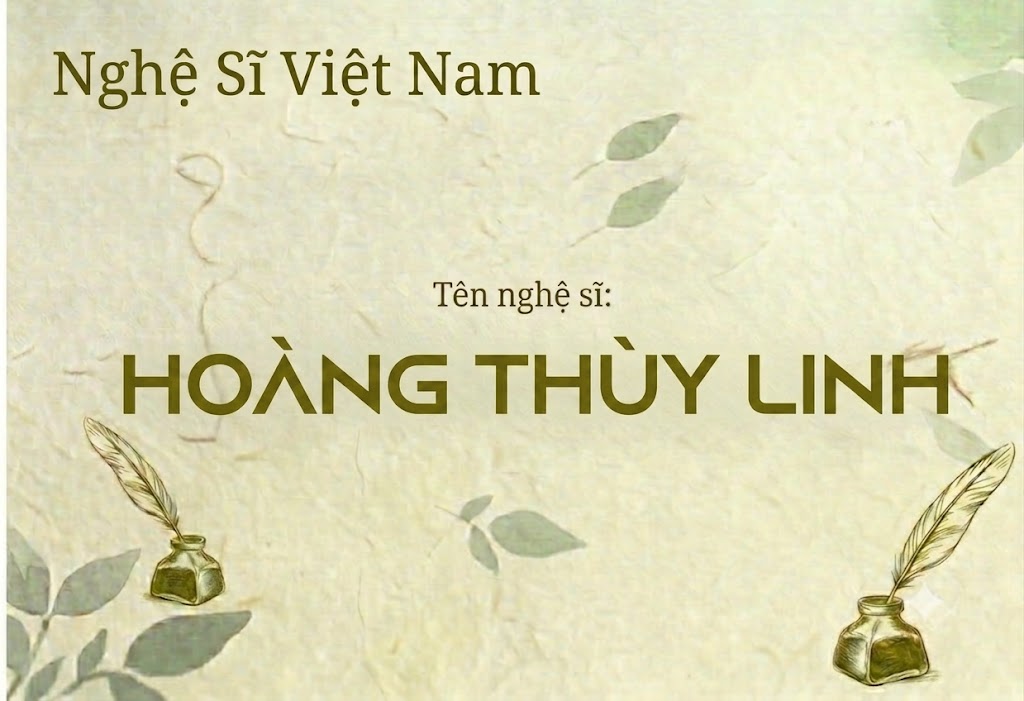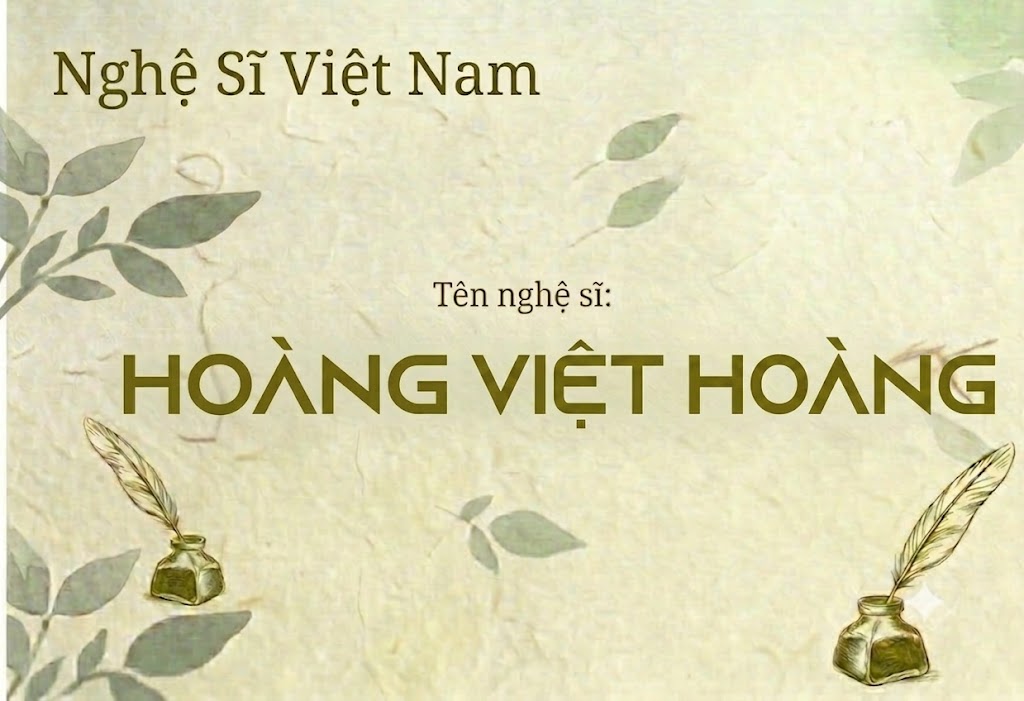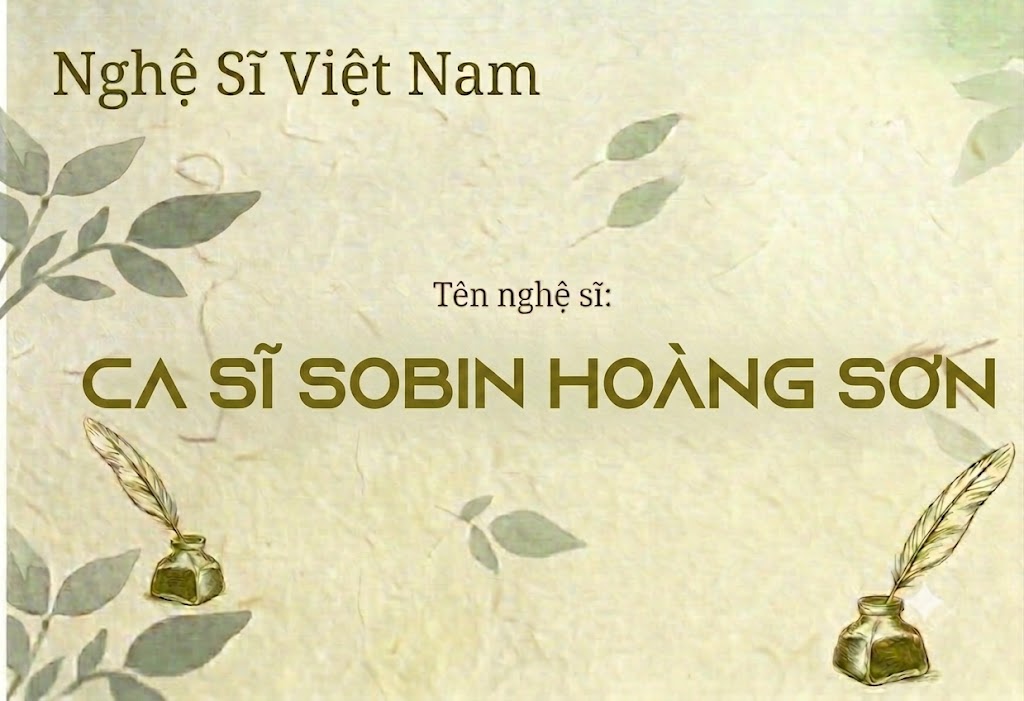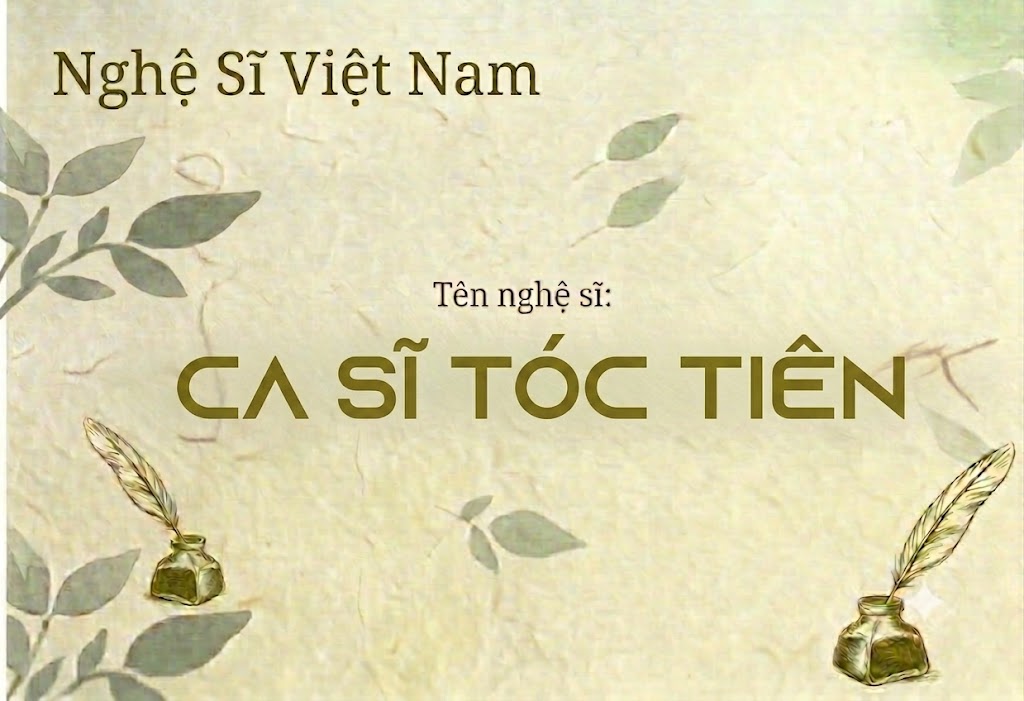
1FTV VIP Azonix
Trong các xu hướng thiết kế đồ họa hiện đại, phong cách tối giản kết hợp với hơi hướng công nghệ tương lai luôn có sức hút mạnh mẽ.
Để tạo nên những ấn phẩm truyền thông độc đáo, việc lựa chọn một phông chữ làm tiêu đề mang tính bứt phá là vô cùng quan trọng.
Nếu bạn đang tìm kiếm một bộ chữ không chân mang phong cách sci-fi đầy hiện đại cho các dự án của mình, thì font 1FTV VIP Azonix chính là sự lựa chọn hoàn hảo.
Giới thiệu về font 1FTV VIP Azonix
Font 1FTV VIP Azonix là một phông chữ display không chân được thiết kế theo xu hướng tối giản và đậm chất công nghệ tương lai.
Đặc điểm nổi bật của phong cách thiết kế Azonix
Sức hút khác biệt của font 1FTV VIP Azonix đến từ cấu trúc hình học vuông vắn kết hợp cùng các đường cắt góc vô cùng táo bạo.
Điểm nhấn độc đáo nhất nằm ở các ký tự như chữ A được cách điệu lược bỏ thanh ngang, tạo nên phom dáng giống như một dấu mũi tên hướng lên đầy cá tính.
Phông chữ được xây dựng theo định dạng all-caps (viết hoa toàn bộ), giúp tạo ra sự đồng đều tuyệt đối về mặt cao độ và bố cục khi sắp xếp dòng tiêu đề.
Nét chữ có độ dày vừa phải, khoảng trống bên trong được tính toán khoa học giúp văn bản luôn giữ được sự thanh thoát, tinh tế và không bị rối mắt.
Để phông chữ vận hành mượt mà trên hệ thống máy tính, phiên bản font 1FTV VIP Azonix đã được xử lý kỹ lưỡng về mặt thông số kĩ thuật.
Hệ thống khoảng cách chữ và độ giãn dòng đã được căn chỉnh chuẩn xác, giúp các từ hiển thị liền mạch và đẹp mắt trên mọi phần mềm biên tập.
Bên cạnh bộ chữ cái viết hoa đồng bộ, phông chữ còn tích hợp đầy đủ dãy số từ 0-9 cùng hệ thống các ký tự đặc biệt, dấu câu thông dụng (.,;: ' " (!?) +-*/=).
Đặc biệt, bản Việt hóa này giúp bạn hoàn toàn yên tâm sáng tạo các nội dung tiếng Việt mà không lo gặp phải tình trạng lỗi font hay lệch dấu.
Hình ảnh demo thực tế của font 1FTV VIP Azonix
Để giúp bạn dễ dàng hình dung khả năng co giãn và hiển thị linh hoạt của phông chữ này trên các kích thước khác nhau, hãy cùng xem qua bảng mô phỏng thực tế:
Kích thước nhỏ (12pt – 24pt): Các nét chữ công nghệ và dấu tiếng Việt vẫn hiển thị rõ ràng, ngay ngắn, dễ đọc trên màn hình điện thoại di động.
Kích thước lớn (36pt – 72pt): Đây là không gian lý tưởng để font chữ phô diễn sức mạnh hình khối không gian, tạo hiệu ứng thị giác hiện đại cho các tiêu đề chính.
Ứng dụng của font Azonix trong thiết kế đồ họa và làm video
Sở hữu nét cá tính bứt phá và mang đậm chất tương lai, font 1FTV VIP Azonix mở ra không gian ứng dụng rộng lớn cho các dự án truyền thông:
Thiết kế thumbnail Youtube và ảnh thu nhỏ: Hoàn hảo cho các video thuộc chủ đề công nghệ, vũ trụ, gaming, khoa học viễn tưởng hoặc review đồ điện tử.
Làm tiêu đề video ngắn (Tiktok, Shorts, Reels): Cấu trúc chữ độc lạ giúp các câu từ khóa chính, tiêu đề mở đầu video trở nên vô cùng bắt mắt và giữ chân người xem.
Banner và poster quảng cáo sự kiện: Thích hợp cho các poster giới thiệu sản phẩm công nghệ cao, banner giải đấu thể thao điện tử (esports) hoặc bìa album nhạc cá tính.
Nhận diện thương hiệu phong cách tối giản: Phù hợp làm logo dạng chữ khối cho các thương hiệu thời trang hiện đại, studio sáng tạo hoặc các công ty khởi nghiệp công nghệ.